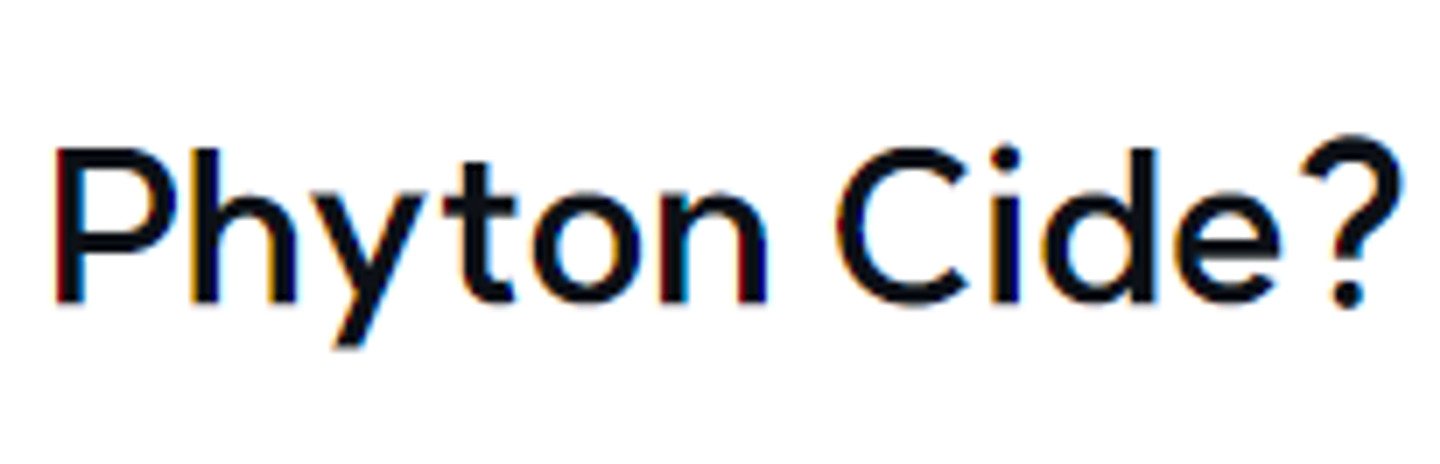
정말 자주 쓰이는 폰트인데 정확하게 어떤 폰트일까요 설명구 글밥이 좀 많아 저 폰트를 써야해서요~
フリーテンダード 길형진 (orioncactus)
입니당
スーツ SUNN YOUN
프리텐다드 아닙니다. 로마자/숫자/기호가 다릅니다.
スイート SUNN YOUN
한글 및 괄호까지는 프리텐다드가 맞습니다. 영문과 물음표에 스위트가 사용되었습니다. 다만, 사이트에서 다운로드한 폰트가 눈누에 업로드되어있는 폰트 미리보기와는 조금 다르게 생겼으니 알아보셔야 할 듯 합니다.